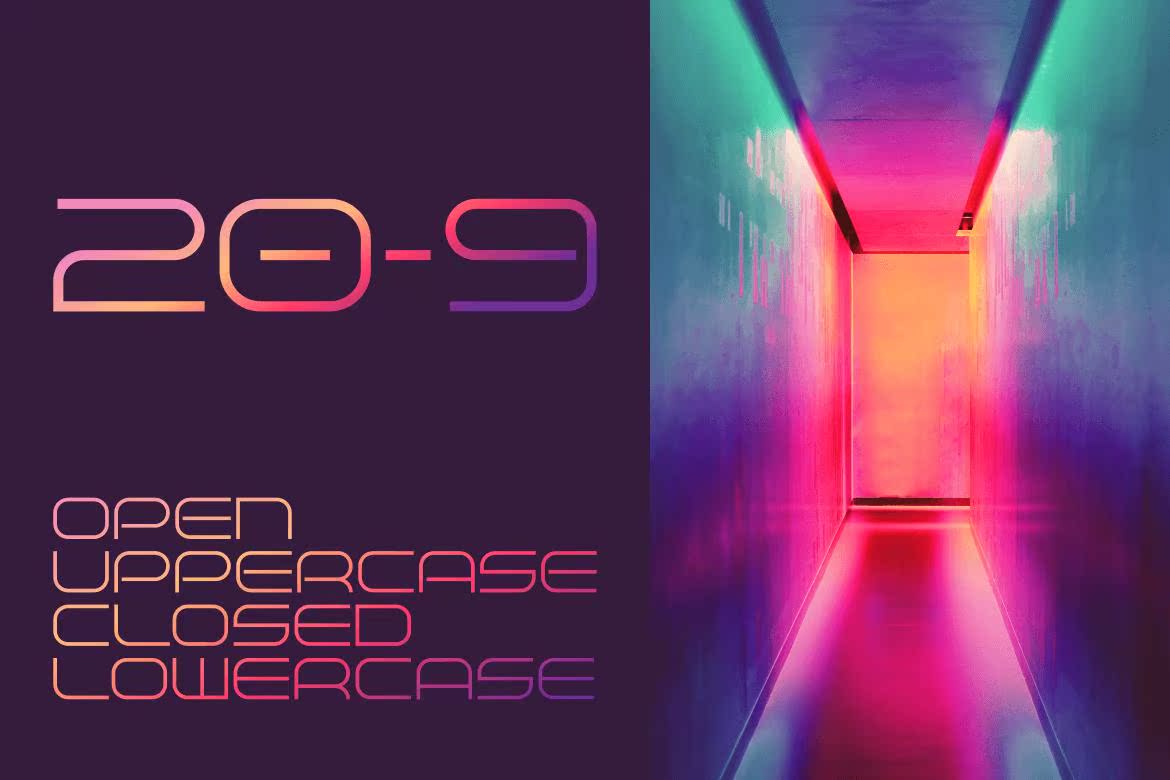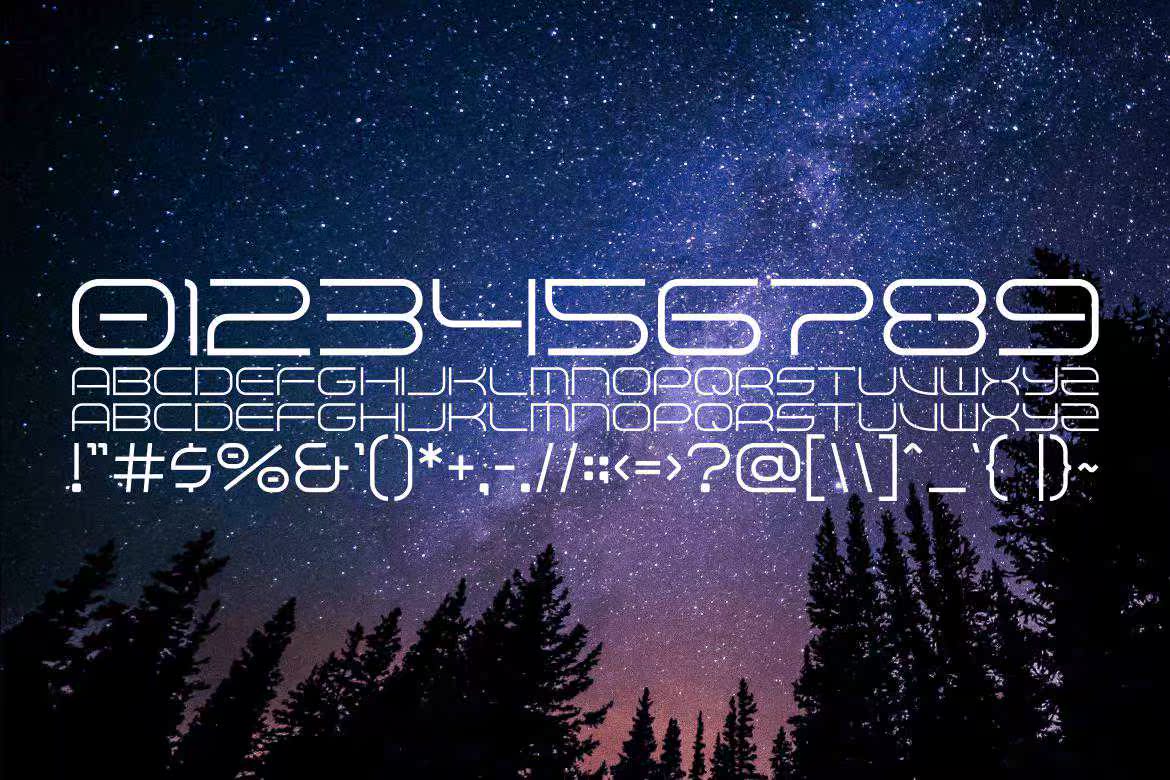
TerbaAngisageMetricWideFontwithThinline,反映了现代技术和未来。非常适合高端文章标题、空间和数字相关项目。大写有一个连接模型,而小写有一个封闭版本。TerbaAngisageMetricWideFontwithThinline,反映了现代技术和未来。非常适合高端文章标题、空间,和DigitalRelatedProject。大写字母有一个开放的连接模型,而小写字母有一个封闭的版本。